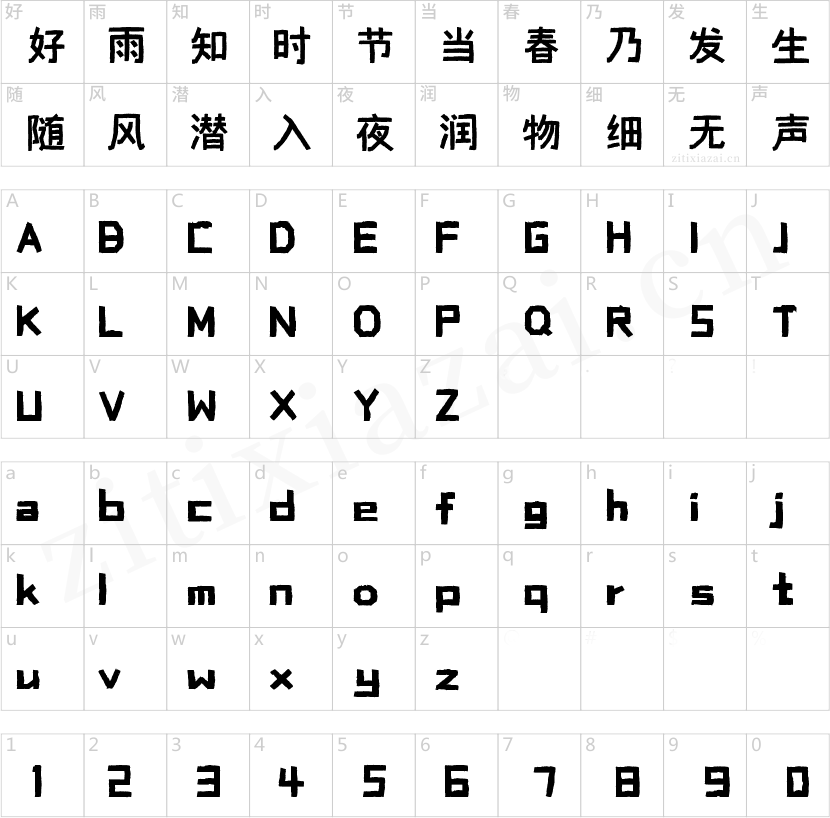
壹心波纹黑
壹心波纹黑,这款字体结构工整、笔画清晰,兼顾美观与易读性,适用于标题、正文、海报、包装、LOGO 等多种场景。字形优雅稳定,风格百搭耐看,适配日常排版与创意设计,让文字呈现更舒适、更具质感。壹心波纹黑一笔一画,皆是细节,以均衡的比例、流畅的线条打造舒适视觉体验,字形端正大气,风格简约现代。无论是商业设计、品牌宣传还是日常排版,都能轻松驾驭,让文字更有格调与力量。壹心波纹黑字体下载。